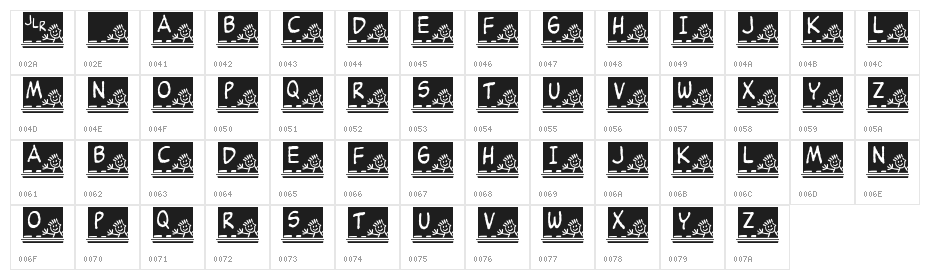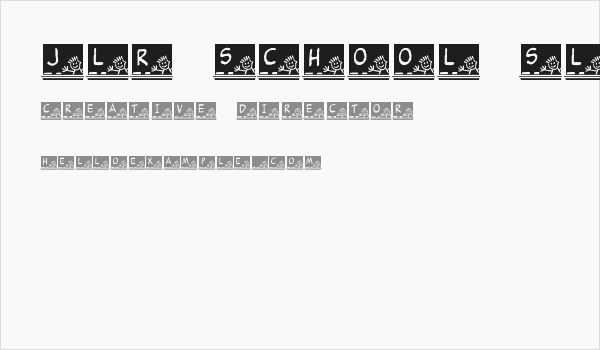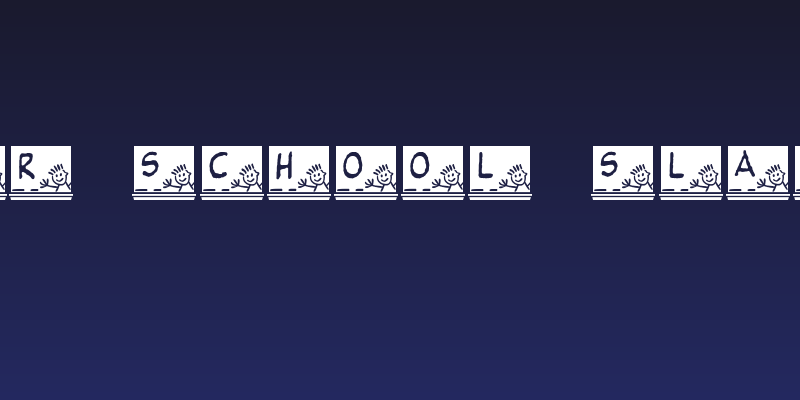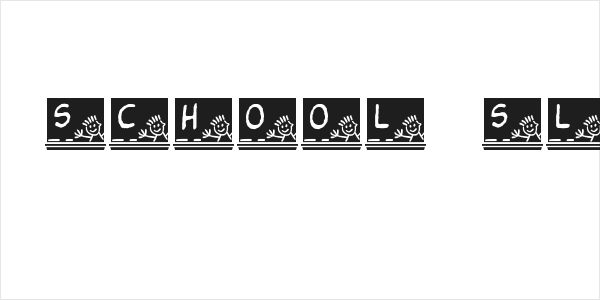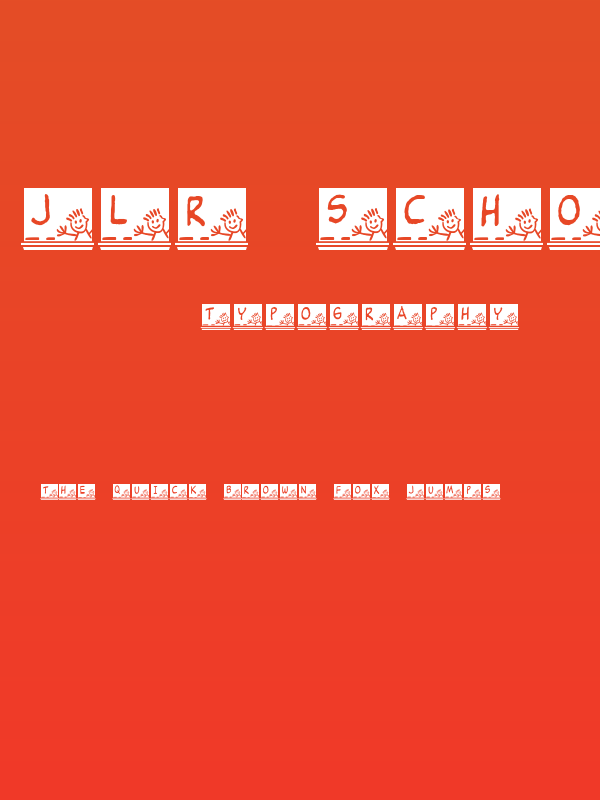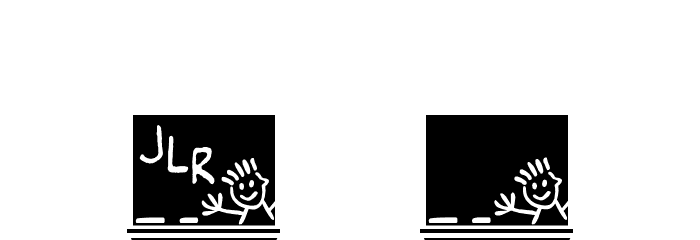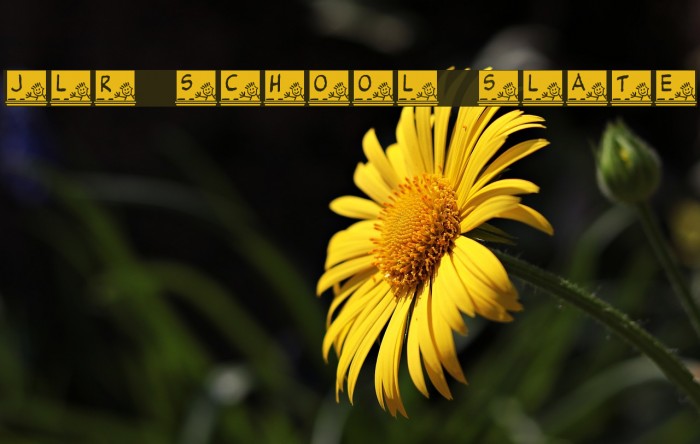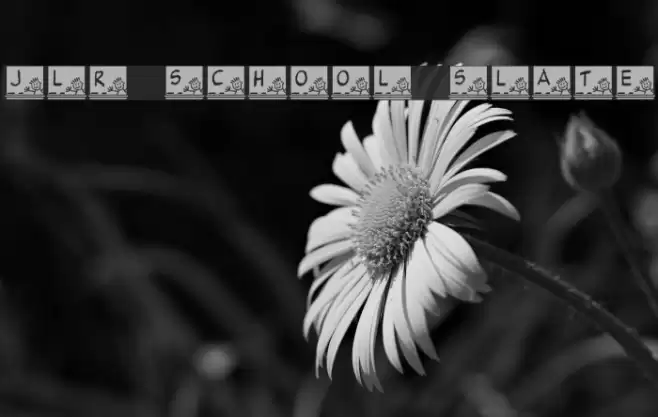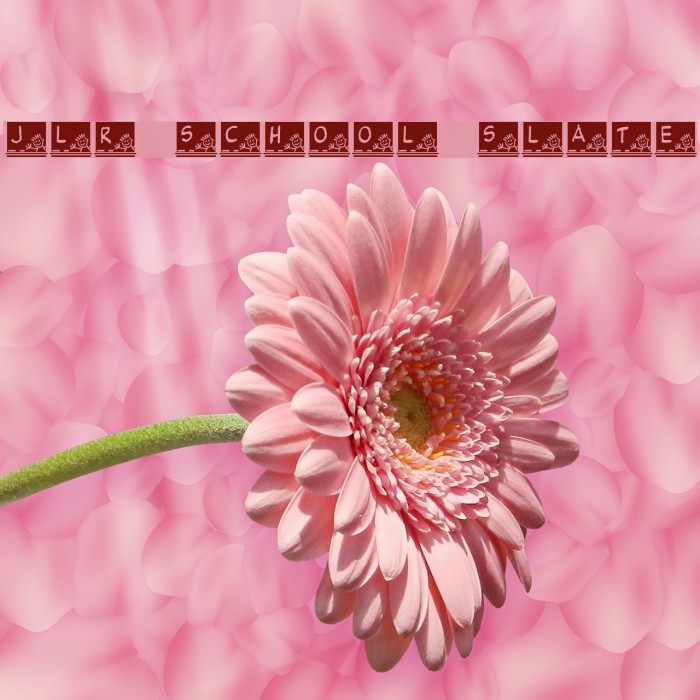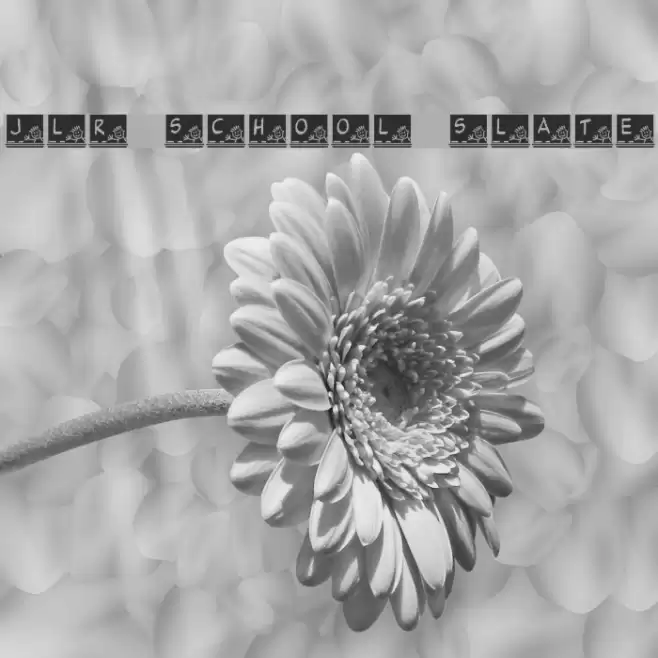
JLR School Slate Font
| Gesamtstil | Playful, Educational |
| Vorgeschlagene Projekte | Ideal for children's books, educational materials, school event posters, and playful branding. |